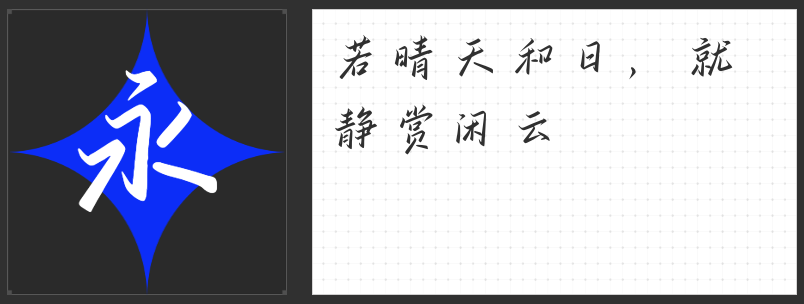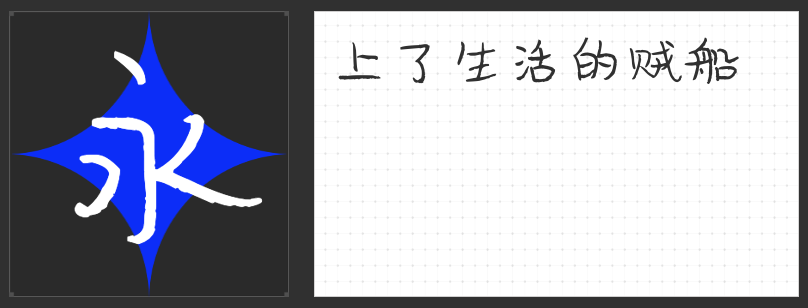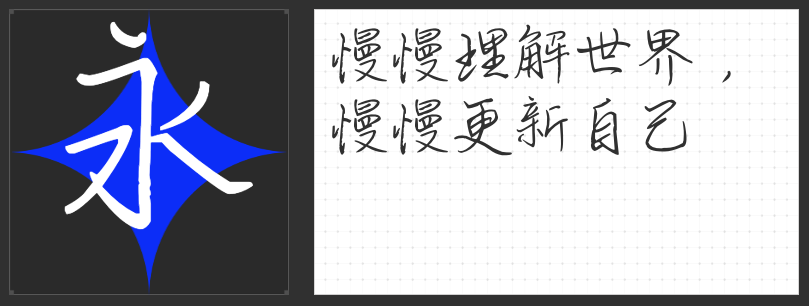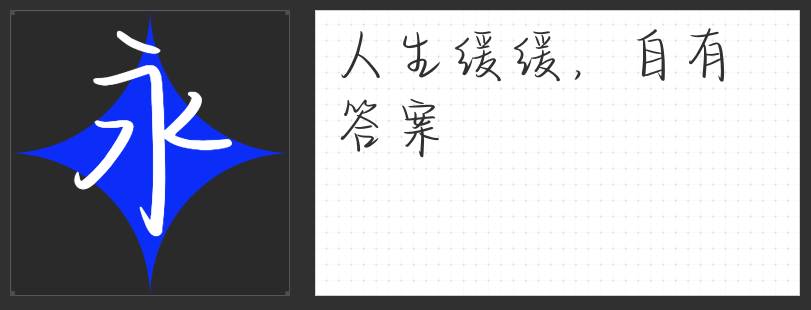
笔触间的艺术之旅:硬笔手写字体推荐
在数字化时代,手写字体的魅力依旧不减,尤其是硬笔手写字体,以其独特的韵味和实用性,成为了许多人心中的挚爱。今天,就让我们一起踏上这场笔触间的艺术之旅,探索几款值得推荐的硬笔手写字体。
首先,我们要介绍的是励字禅意简,其文艺的手写风格,展现了字形端正而不失笔画的随性。每一笔一划都透露出书写者的从容与自在,仿佛是在纸面上进行的一场心灵修行。其字体设计简约而不失细节,既保留了传统书法的韵味,又融入了现代设计的审美,使得整体风格既古典又时尚。
这款字体特别适合用于需要营造轻松、随意、佛系氛围的场合。无论是茶艺馆的菜单设计、休闲场所的装饰布置,还是个人笔记、手账的书写记录,励字禅意简都能完美融入其中,为作品增添一份独特的禅意与雅致。
接下来是也字工厂梦洄手迹体,这是一款融合了复古与现代元素的硬笔手写字体。它的设计灵感源自于对传统手迹的深刻理解与现代审美的巧妙结合,既保留了手写字体的自然与随性,又赋予了其新的生命与活力。这款字体在笔画上追求流畅与变化,每一笔都仿佛蕴含着书写者的情感与思绪,让人在欣赏之余,也能感受到一份温暖与亲切。
在视觉呈现上,也字工厂梦洄手迹体展现出了极高的辨识度与美感。其字形结构独特而不失和谐,笔画粗细有致,整体风格既复古又不失时尚感。这种独特的视觉效果,使得这款字体在各类设计作品中都能脱颖而出,成为吸引眼球的焦点。
再来看MyFont凌渡猪猪简,这款字体在保持硬笔手写的基本特点的同时,融入了卡通元素,使得每一个字都仿佛拥有了生命,跃然纸上。其笔画圆润饱满,线条流畅自然,给人一种温馨、亲切的感觉。尤其是那些不规则的弧度和小巧的装饰,更是增添了几分童趣和萌态。MyFont凌渡猪猪简用可爱的形态和温馨的笔触,传递出对生活的热爱和对美好的追求。
最后,不得不提的是也字工厂雨眠手迹,这款字体仿佛是在一个细雨绵绵的夜晚,由一位文人墨客悠然自得地书写而成。它的每一笔一划都透露出一种从容与淡雅,如同雨丝轻拂过心田,带来一丝丝清凉与宁静。字体结构既保留了传统书法的韵味,又融入了现代设计的简约与流畅,使得整体风格既古典又不失时尚感。
无论是用于书籍封面、海报设计,还是个人笔记、手账记录,也字工厂雨眠手迹都能完美融入其中,为作品增添一份独特的韵味与深度。它不仅能够提升作品的整体质感与美感,更能传递出一种宁静致远的情感与意境。
总之,硬笔手写字体以其独特的魅力和实用性,在数字化时代依然占据着一席之地。无论是追求传统韵味还是展现个性创意,都能在这些字体中找到心仪之选。